Webフォントのデザインテクニック01「見出しやリード文を詰め組みしよう」
見出しやリード文など、文字サイズが大きいために文字間が目立つ場合や、文の視覚的なまとまりが欲しい場合は、詰め組みするとより綺麗に見せることができます。
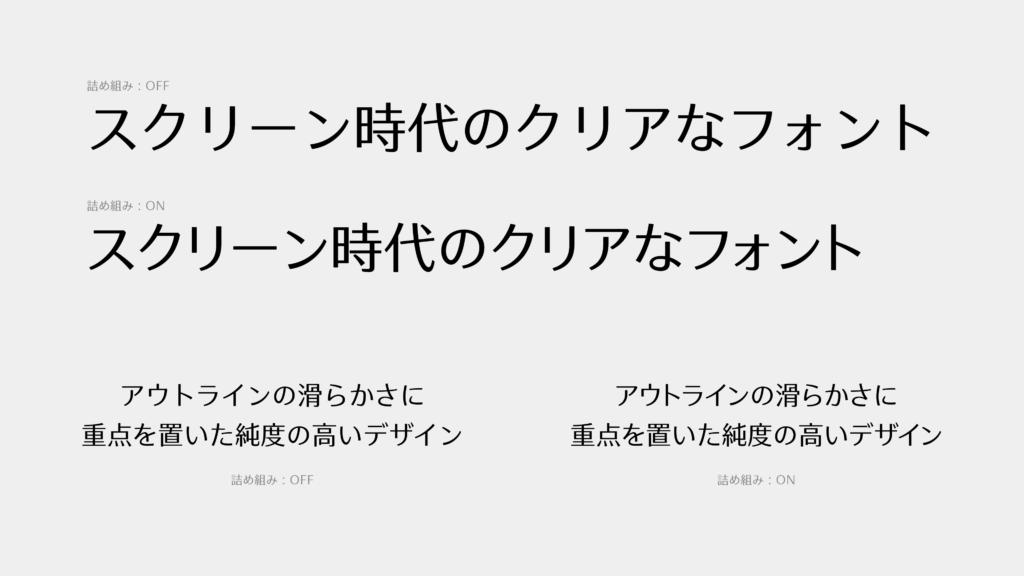
OpenType フォントは、文字の形状だけでなく、文字組版に関するさまざまな機能についての情報を含んでいます。
このうち、paltとkern(縦組みの場合はvpalとvkrn)という OpenType 機能を利用することで、Web フォントでも詰め組みすることができます。
palt/vpalは、全角グリフの文字幅を文字ごとに適切に設定する(プロポーショナル)機能です。
上が何もしていないもの、下がpaltを適用したものです。
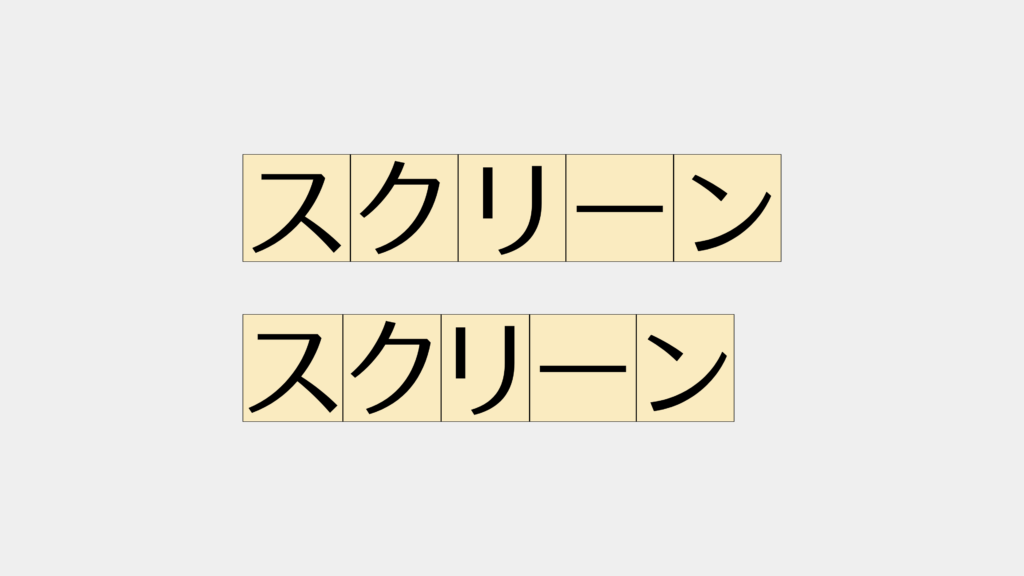
kern/vkrnはグリフ間のスペースが均一になるように、グリフの位置を調整する(カーニング)機能です。
上の青い文字がpaltのみ、下の赤い文字がpaltとkernの両方を適用したもの、中央はそれら2つを重ねたものです。kernにより位置が調整されていることがわかります。
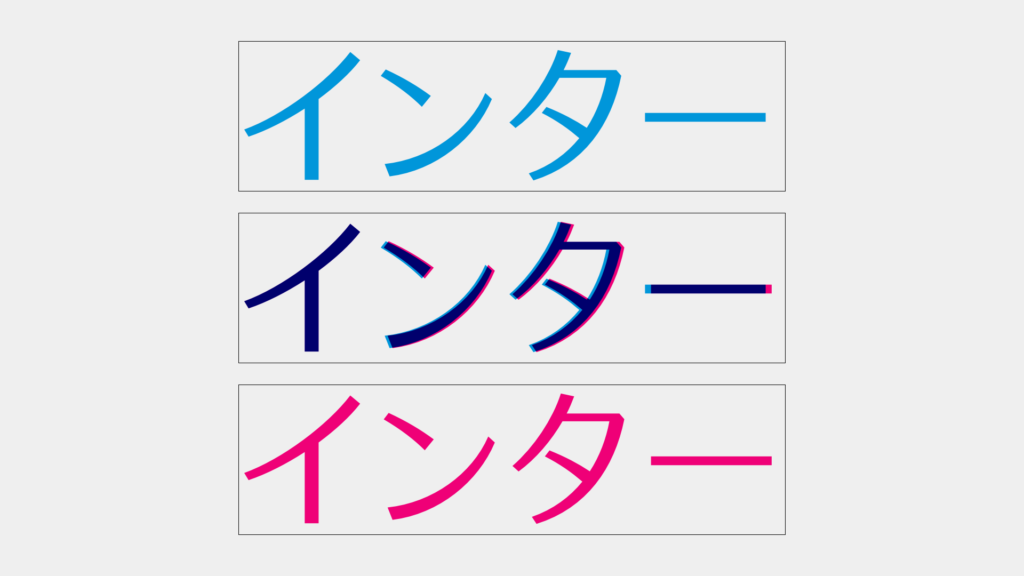
※主要なブラウザでは、kernはfont-kerningプロパティのauto値によって、デフォルトで適用されています。しかし、日本語 OpenType フォントの kern/vkrn 情報は、 palt/vpal が適用されていることを前提に設定されているので、2つ合わせて設定する必要があることに注意してください。
Web フォントでこれらの OpenType 機能を利用するには、font-feature-settingsプロパティを利用します。
今回の詰め組みでは、横組の場合は
font-feature-settings: "palt", "kern";
縦組みの場合は
font-feature-settings: "vpal", "vkrn";
と指定すると、詰め組みを実現できます。
ちなみに、これらを利用すると letter-spacing で文字間を空けて組むときにも、より均一な空き具合にすることができます。
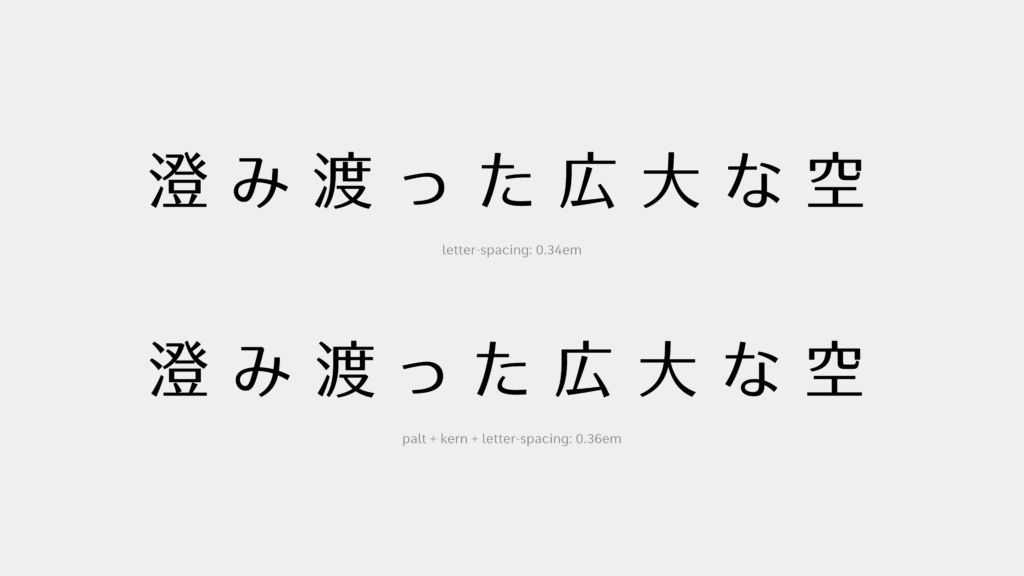
palt や kern は便利な機能ですが、長めの文に適用すると、文字のリズムが不均一になってしまい読みづらくなるため、本文への適用はおすすめしません。
また、これらの OpenType 機能はフォントによっては実装していないものもあります。